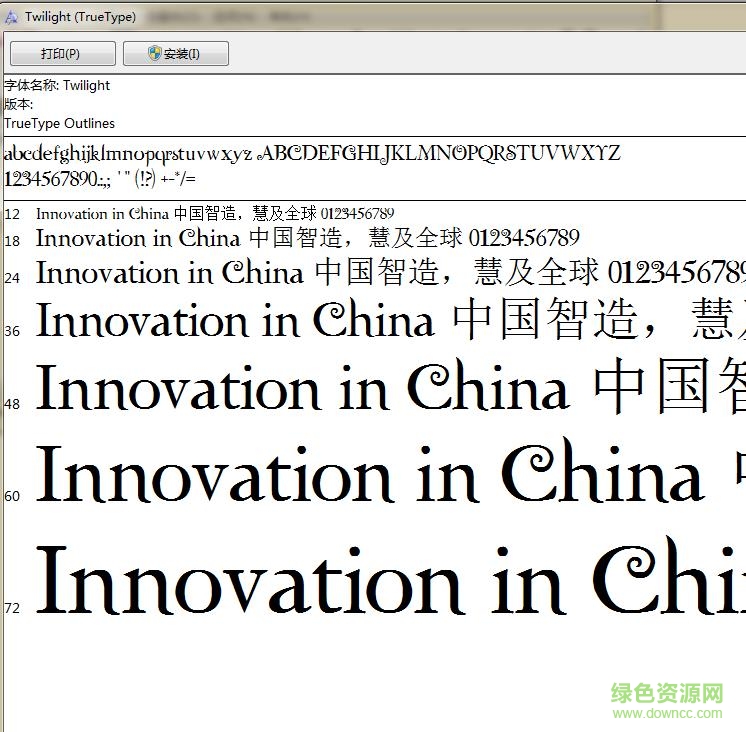
twilightscript字體ttf
twilight script英文字體的特色在于字體的每一個(gè)字母都擁有回旋向上的獨(dú)特字體格式,十分優(yōu)美,讓你在使用的過程中能夠感受到濃濃的獨(dú)家效果,帶給視覺強(qiáng)大的沖擊體驗(yàn),快來綠色資源網(wǎng)下載吧!
twilight script字體小編點(diǎn)評
這款字體在字體的轉(zhuǎn)彎以及筆落,起筆的的過程中都擁有扭曲的感覺,讓你隨便運(yùn)用在各種場合以及word文檔中都能夠感受到不錯(cuò)的效果!